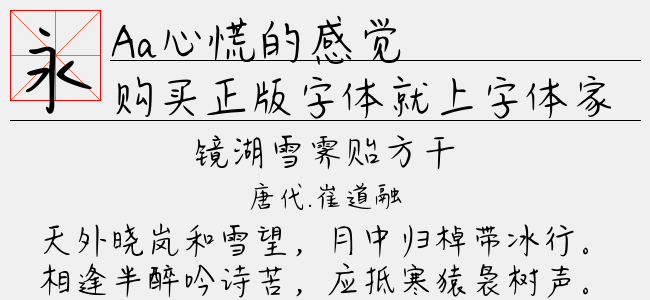
Aa心慌的感觉(5.10 MTTF中文字体下载)
Aa心慌的感觉 字体大小5.10 M,包含了6763个汉字以及附加其他英文字体和阿拉伯数字,属于Aa字体。Aa心慌的感觉(TTF)可以免费下载,商业用途请自行购买版权,它的特征就是手写,手书风格,行书,钢笔,采用安装嵌入的安装方式,支持符号拉丁文日文中文等语言
字体作者:Aa字体
字体名称:Aa心慌的感觉